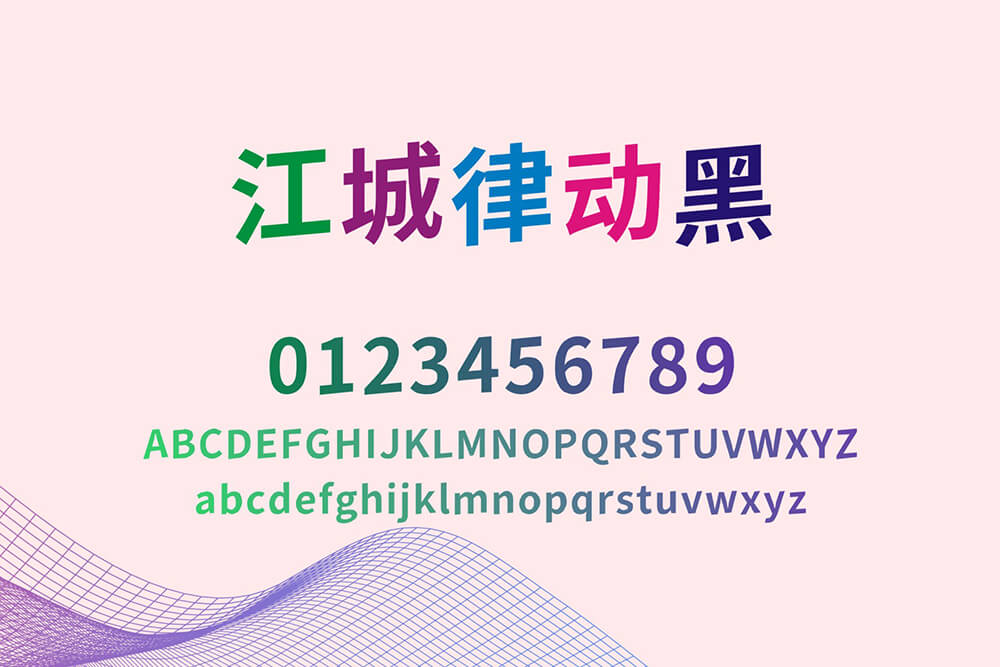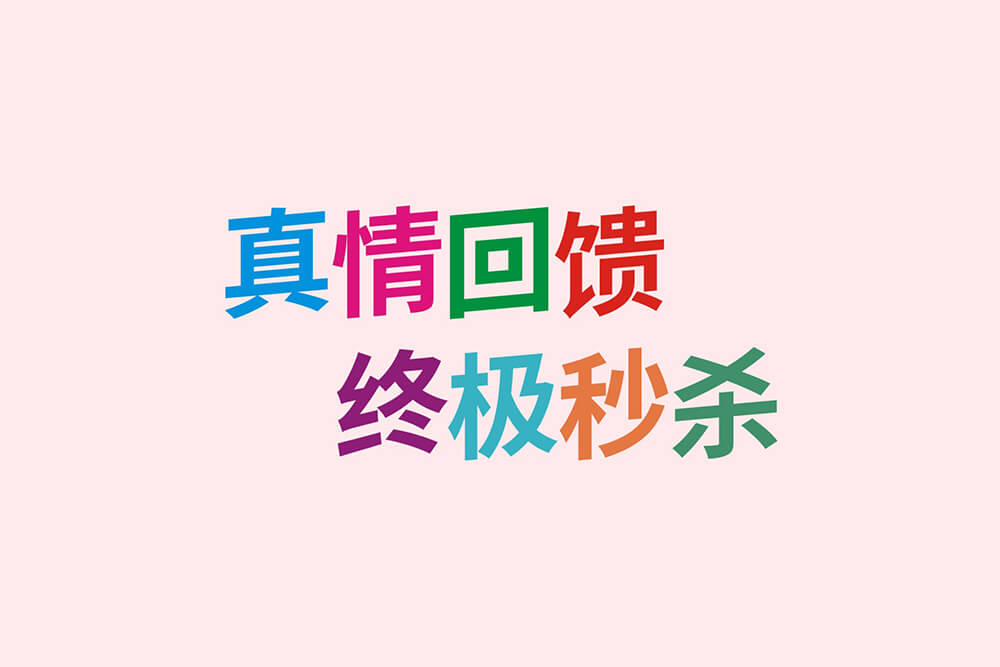
江城律动黑是一款基于思源黑体 Bold 改造的免费可商用中文黑体字体。在保留黑体稳重、清晰的笔画骨架上,整体字形向左倾斜约 5 度,赋予了字体律动感,特别适合活动海报、促销广告、品牌标语等需要吸引眼球的场景。
江城律动黑包含 GB2312 全部 6763 个汉字,并覆盖繁体、英文、韩文、日文、数字及符号等,可以满足各种设计需求。尤其是大号字、短标题这种,适当缩小一下字间距,律动效果会更紧凑、更有张力。